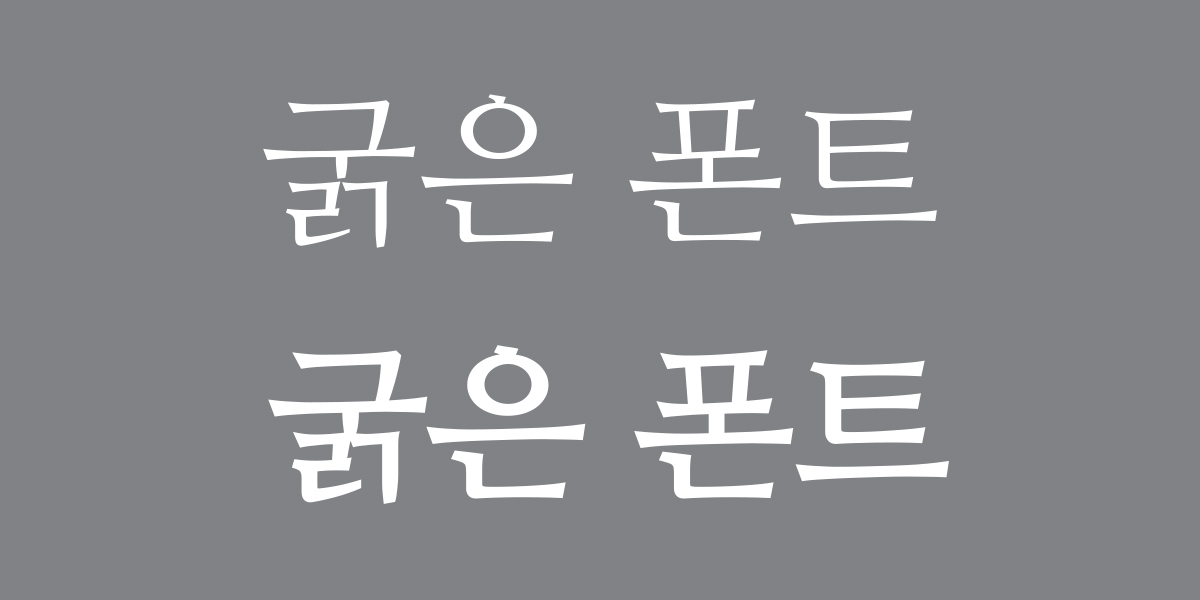
일러스트레이터 폰트 굵기 조정하기
일러스트레이터에서 폰트 굵기를 조정하는 경우는 로고를 디자인하거나 포스터를 디자인할 때 제목의 글자를 강조하기 위해서 많이 사용하는 방법입니다.
이때 사용하는 각 폰트들의 볼드 서체를 사용하기도 하지만 볼드 폰트를 지원하지 않는 폰트에 더 임팩트 있는 두꺼운 볼드 폰트를 만드는 방법이 있습니다. 일러스트레이터에서 굵은 폰트를 만들기 위해 '굵은 폰트'라고 텍스트를 생성합니다. 기본 폰트는 나눔 명조 옛 한글 폰트를 사용하였습니다.
나눔 명조 옛 한글 폰트는 Bold를 지원하지 않기 때문에 비교를 위해 바로 아래에 동일한 폰트를 복사하고 이번에는 복사한 폰트에 폰트와 동일한 흰색의 Stroke을 추가하고 Stroke 두께를 5pt로 설정합니다. 이와 같이 간단한 방법으로 볼트 폰트를 지원하지 않는 폰트들의 폰트 굵기를 조정할 수 있습니다.
한글 영어 폰트 굵기
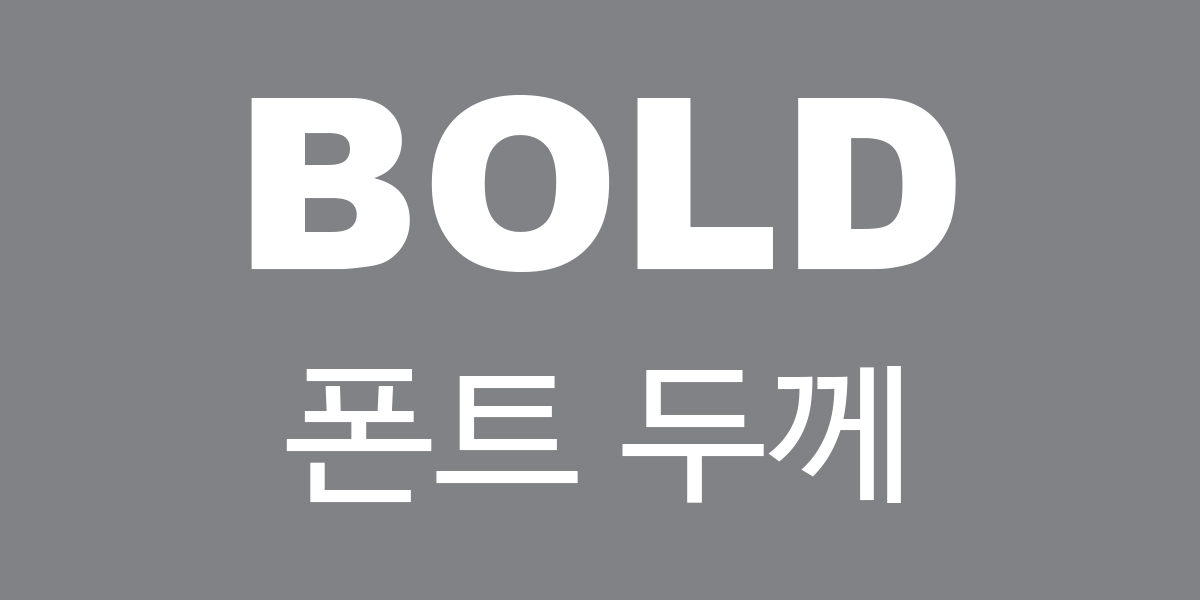
로고를 디자인하는 경우 한글과 영문을 동시에 사용해야 하는 경우가 있습니다. 이때 한글과 영문의 폰트 굵기를 비슷하게 만들어 주는 것이 핵심입니다. 하지만 영문중에 한글을 지원하지 않는 폰트들이 있는 경우 한글 폰트를 조정하여 영문 폰트와 동일한 굵기로 수정할 수 있습니다.
이 작업을 위해서 우선 일러스레이터에서 굵은 영문과 한글 폰트를 만들기 위한 샘플로 영문 'BOLD' 폰트와 한글 '폰트 두께'를 만듭니다. 영문 폰트는 Arial-Black폰트를 사용하였으며 한글 폰트는 나눔 바른 고딕을 사용하였습니다. 두 폰트 굵기가 전혀 다른 것을 확인할 수 있습니다.
영문을 기준으로 한글 폰트의 두께를 조정하기 위해 한글 폰트를 선택하고 폰트와 동일한 흰색의 Stroke을 추가하고 Stroke 두께를 11pt로 설정합니다. 영문과 동일하도록 폰트의 굵기와 느낌을 더 통일하기 위해서는 한글의 글자 간격을 조정해 주는 것이 좋습니다.
그 이유는 기본적으로 한글은 영문보다 글자의 간격이 좁기 때문에 한글 폰트 전체를 선택하고 폰트의 글자 간격을 100으로 설정합니다. 처음 아무것도 설정하지 않는 상태일 때와 확실하게 다르게 영문과 통일성 있는 한글 폰트의 굵기가 만들어졌습니다. 이와 같은 방법을 응용하면 볼드 폰트를 지원하지 않는 폰트들을 활용하여 다양한 굵은 폰트 디자인을 만들 수 있습니다.